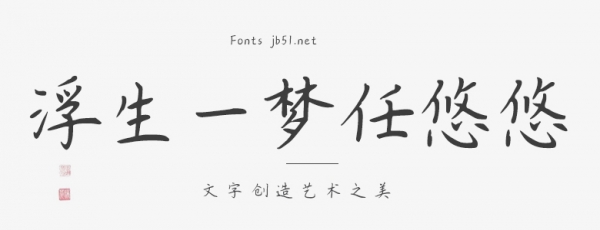
浮生一夢(mèng)任悠悠款字體采用了中國(guó)傳統(tǒng)的書(shū)法藝術(shù)風(fēng)格,如楷書(shū)、行書(shū)等,體現(xiàn)了中國(guó)傳統(tǒng)文化的魅力,適合用于裝飾設(shè)計(jì),如海報(bào)、廣告、書(shū)籍封面等,能夠?yàn)樽髌吩鎏硪环莨诺漤嵨?